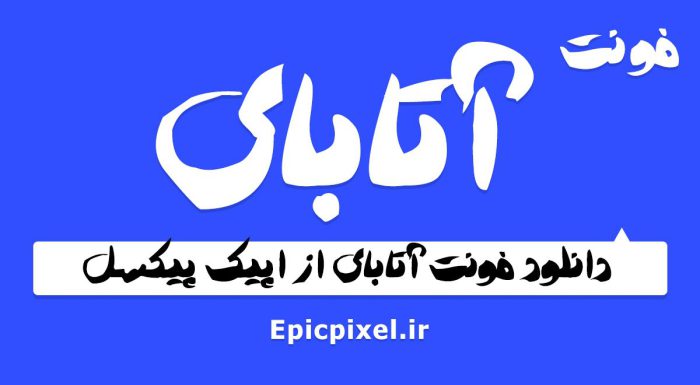
اگر به دنبال یک فونت فارسی هستید که بتواند در طراحی های خودتان هویتی منحصر به فرد ایجاد کند، فونت آتابای می تواند انتخابی بی نظیر باشد. این فونت با الهام از سبک قلم مو و جوهر طراحی شده و توانسته است پیوستگی خط فارسی را با روحیه شرقی به صورتی دلنشین ترکیب کند
. اگر قصد دارید در پروژه های خود حسی هنری و اصیل ایجاد کنید، این فونت با ظاهری نمایشی و کنتراست بالا می تواند طراحی های شما را به یک اثر بصری تبدیل کند.
یکی از ویژگی های برجسته فونت آتابای ، شخصیت قوی و نمایشی آن است که به راحتی توجه مخاطبان را به خود جلب می کند
. این فونت برای لوگوها، بنرها و حتی طراحی جلد کتاب ها بسیار مناسب است و به دلیل طراحی دست نویسش، گرمی و صمیمی گی خاصی به کارهای شما می بخشد
. اگر به دنبال ایجاد طرح هایی هستید که در میان دیگران برجسته و متمایز باشند، این فونت می تواند ابزاری قدرتمند در اختیار شما قرار دهد.
علاوه بر زیبایی، فونت آتابای قابلیت استفاده در انواع پروژه ها را دارد. این فونت در فرمت های مختلفی مانند TTF و WOFF موجود است که آن را برای استفاده در نرم افزارهای گرافیکی و حتی وب سایت ها ایده آل می کند
. اگر به دنبال یک فونت نمایشی با شخصیت قوی هستید، آتابای گزینه ای است که نمی توانید از کنارش بگذرید.
با این فونت، طراحی های شما نه تنها زیبا بلکه بسیار تاثیرگذار خواهند بود.